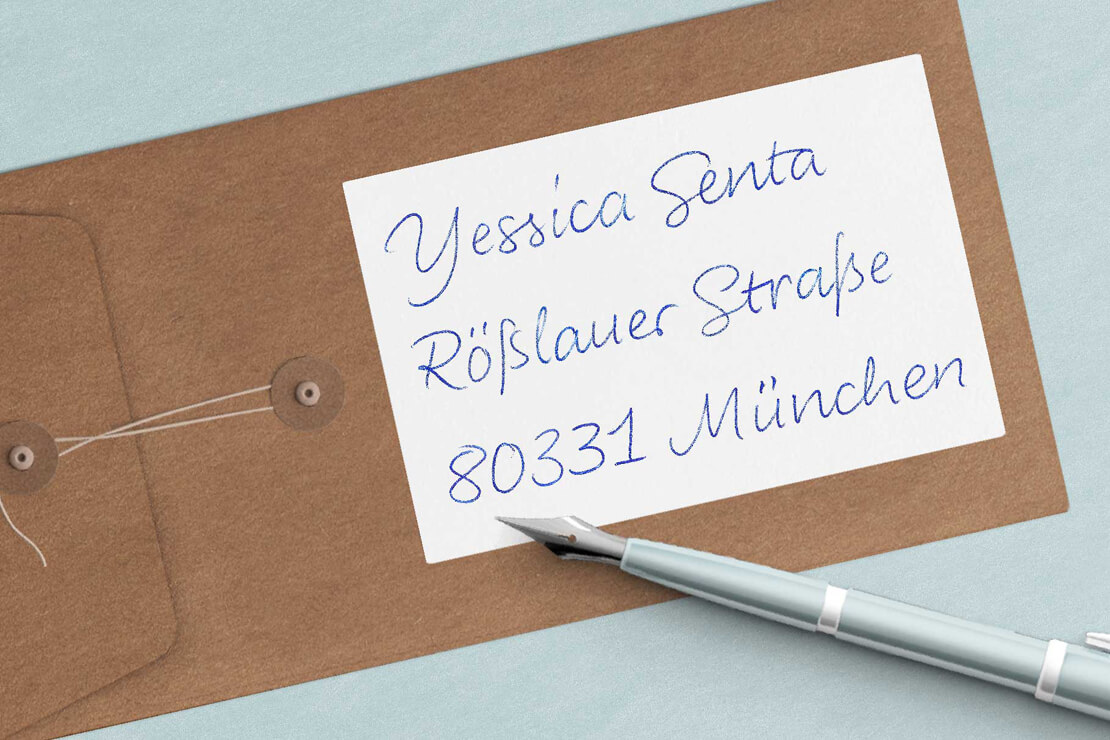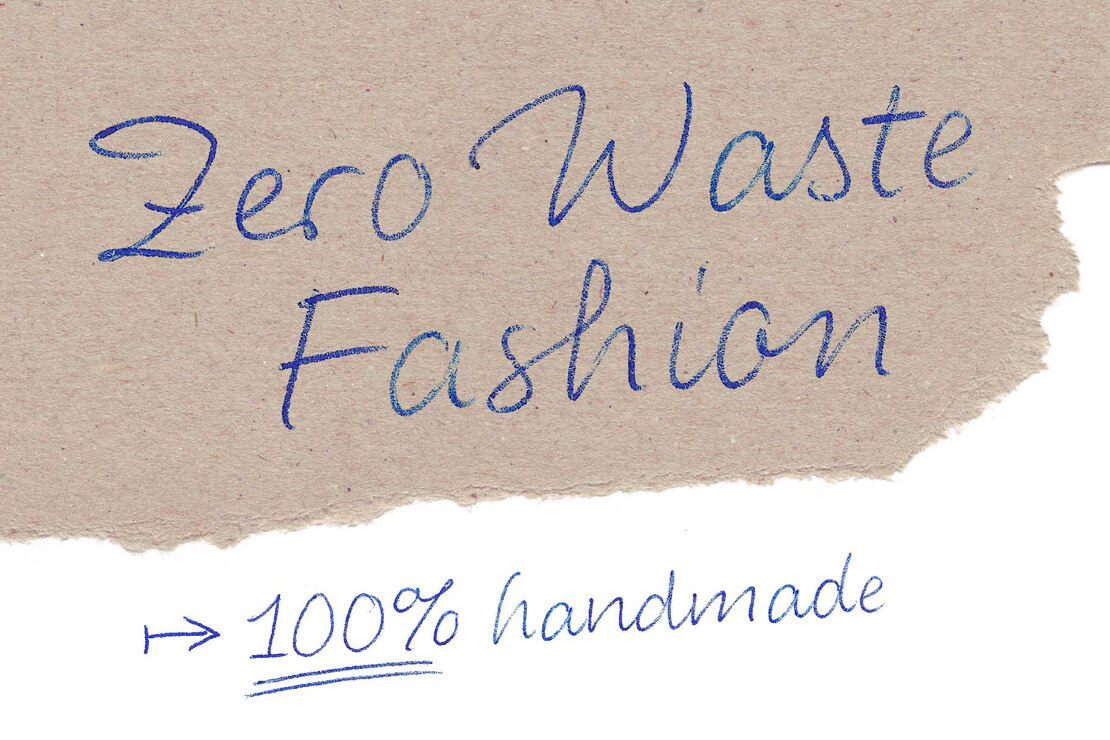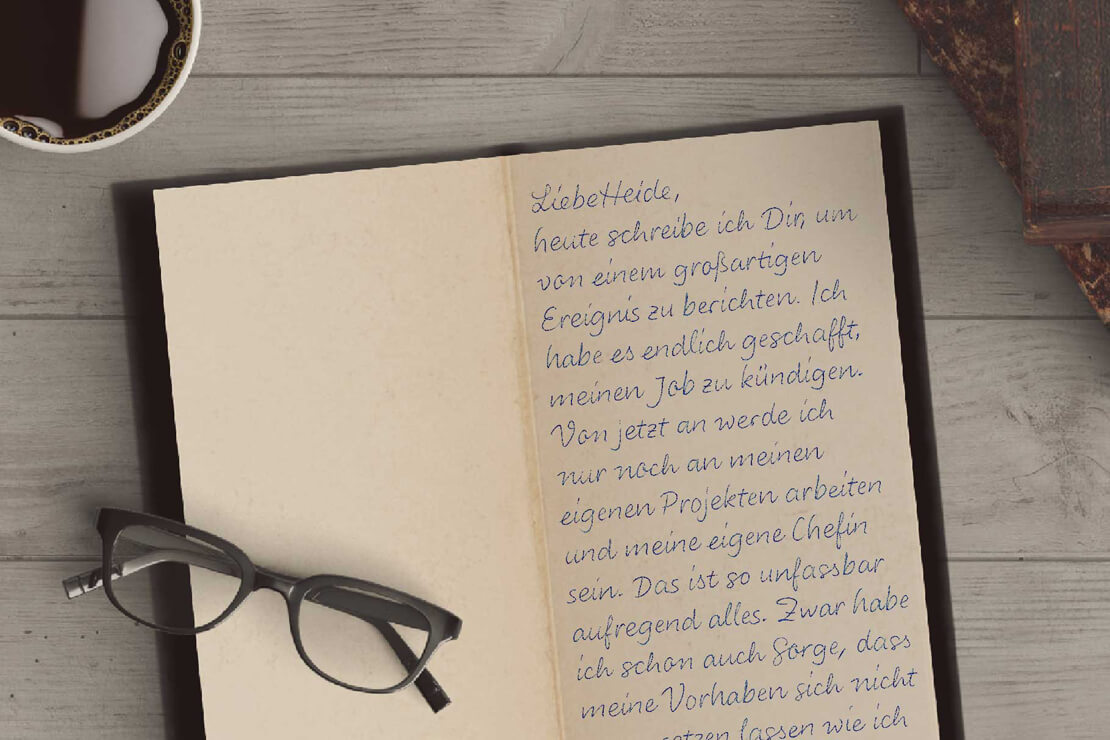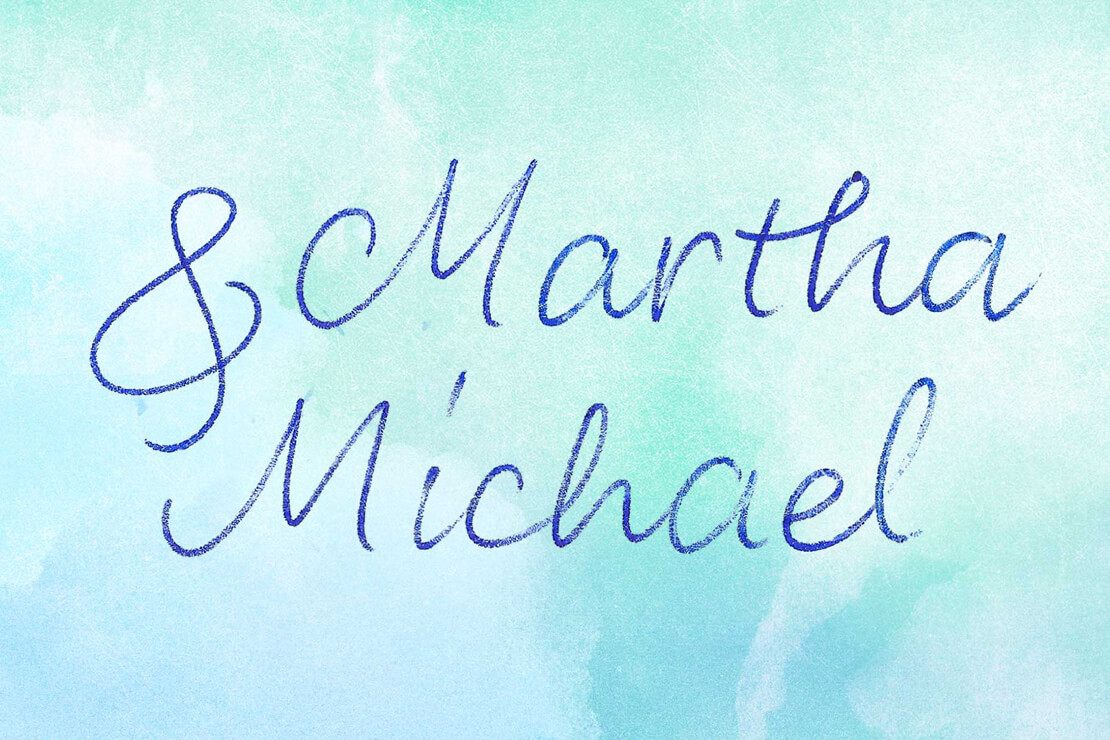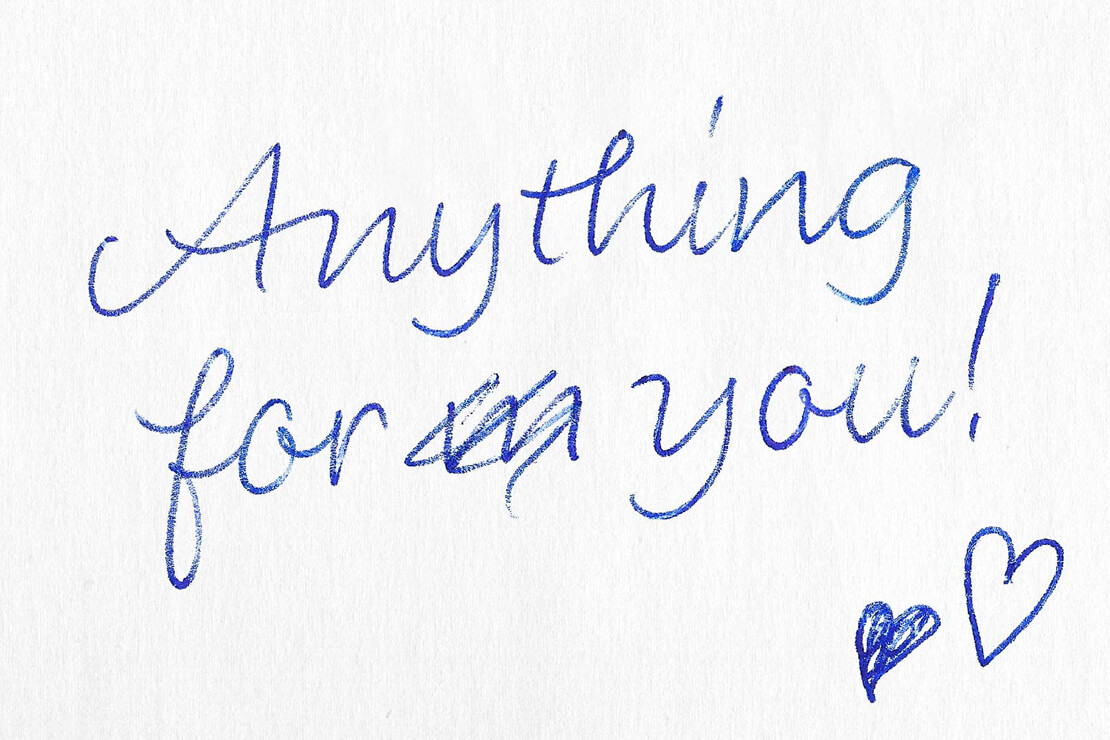
Farbige Kugelschreiber-Schrift
Mit »LiebeHeide« stellt Ulrike Rausch eine Schriftart vor, die das Schriftbild eines Kugelschreibers authentisch nachbildet. Dafür sorgt eine Kombination aus OpenType- und Color-Font-Technologie.
Digitalisierte Handschrift wird zur Kugelschreiber-Schrift
Als Vorlage für den Color-Font LiebeHeide dienten echte Kugelschreiber-Schriftzüge, die Ulrike Rausch hochaufgelöst digitalisierte. Parallel dazu setzte die Kreative zusätzliche OpenType-Features wie beispielsweise Ligaturen oder Alternativbuchstaben ein.
Elemente wie Symbole, Kringel, Unterstreichungen (einfach und doppelt) und jede Menge Durchstreichungen in horizontal, diagonal oder Krickelkrakel-Stil unterstreichen den verblüffend echt wirkenden, handschriftlichen Charakter der Kugelschreiber-Schrift.
Moderne Schrifttechnologie im Kugelschreiber-Font
Viele der Symbole werden außerdem automatisch beim Schreiben zusammengesetzt. Das funktioniert beispielsweise mit einem „<3“ oder „:-)“. Insgesamt kommt LiebeHeide* somit auf fast 500 Glyphen.
Zur Steigerung der Performance sind im Kugelschreiber-Font drei verschiedene Auflösungen hinterlegt, so dass Anwendungen lediglich die Größe laden, die aktuell gebraucht wird.